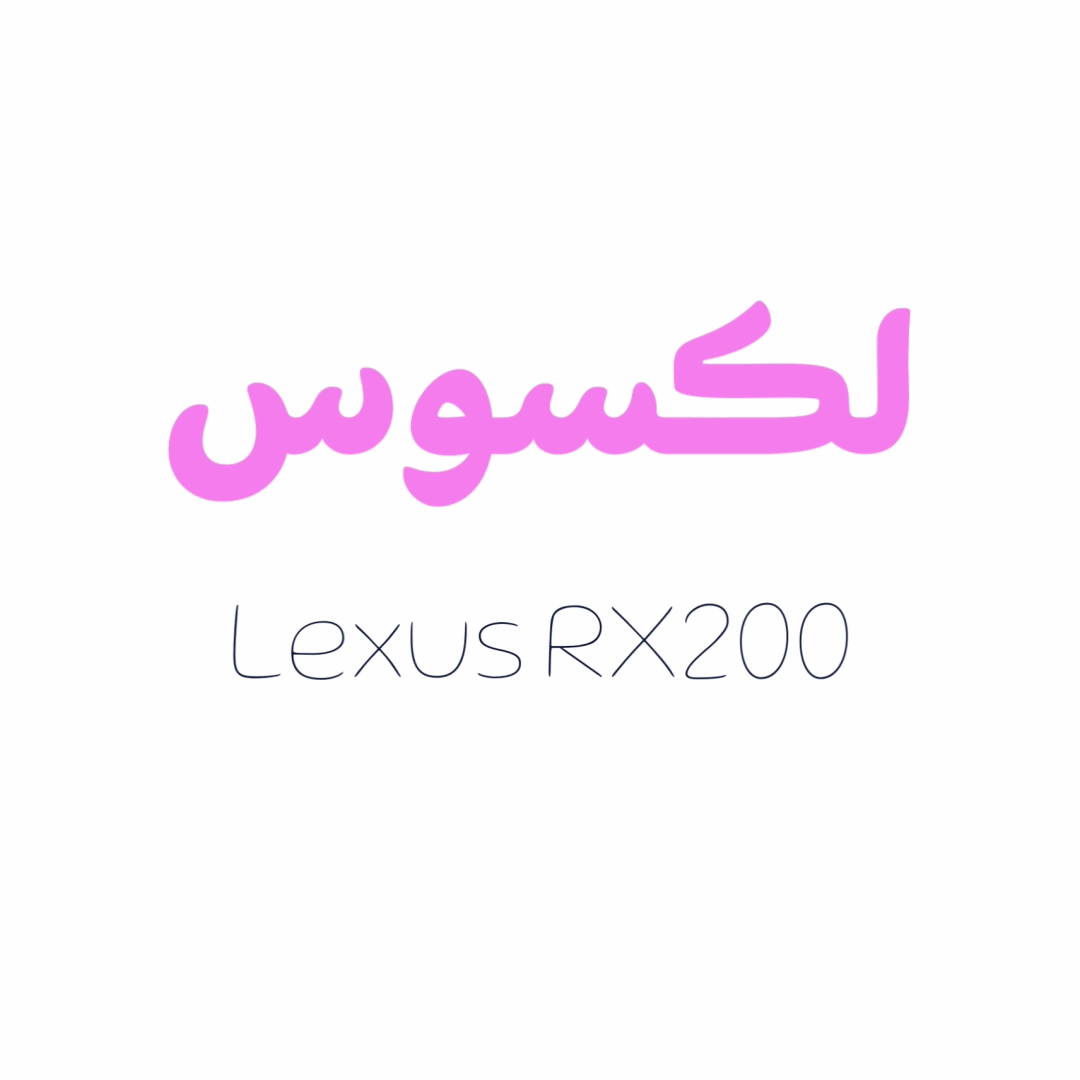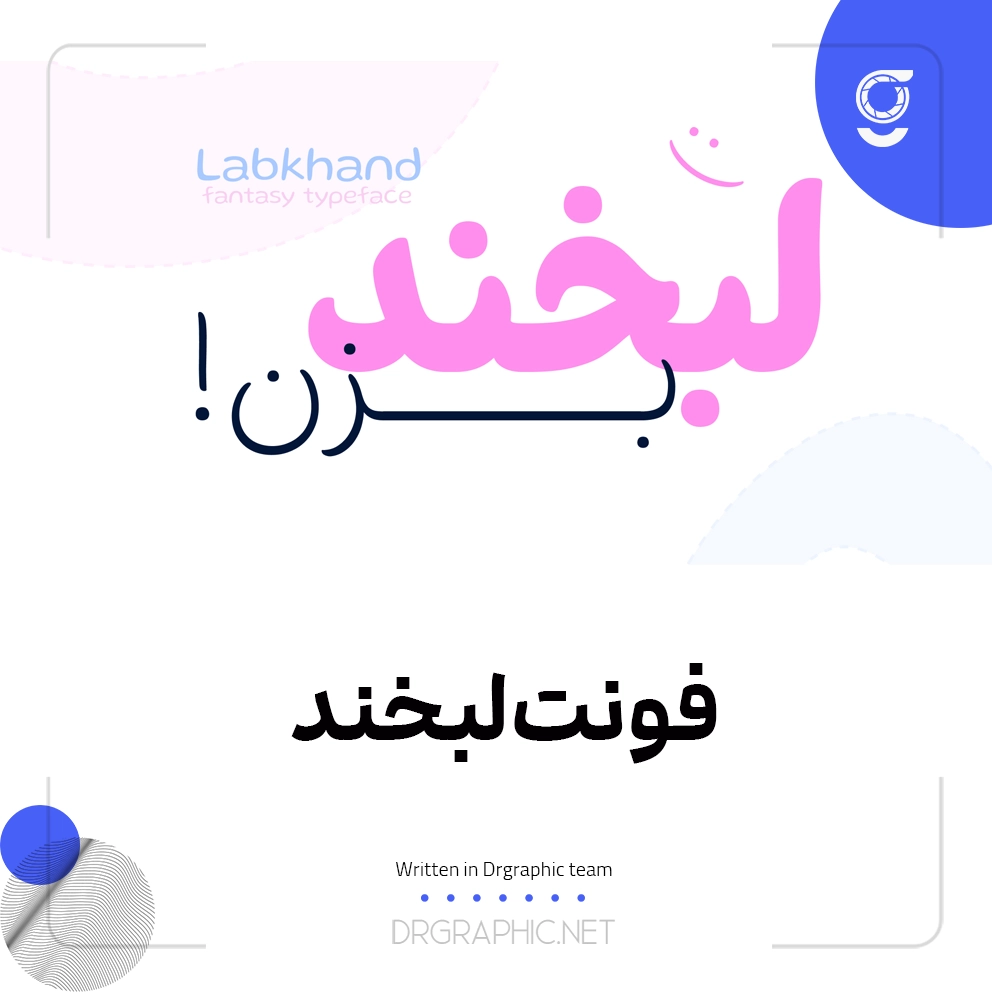
لبخند، یک فونت دستنویس فارسی است که با الهام از سادگی، صمیمیت و حالوهوای نوشتههای شخصی شکل گرفته است.با دکترگرافیک همراه باشید.
در طراحی این فونت تلاش شده تا فرم حروف، حس لطافت و نرمی را حفظ کند؛ بهگونهای که هر کلمه، حالتی زنده، دوستانه و متفاوت داشته باشد.
فونت لبخند، برای استفاده در فضاهایی طراحی شده است که نیاز به حس صمیمیت، انرژی و شخصیت دارند؛ از پوستر و بستهبندی گرفته تا محتوای شبکههای اجتماعی، متنها، عناوین و هویتهای بصری.
لبخند؛ جایی که نوشته، فقط خوانده نمیشود؛ بلکه حس میشود.
فونت لبخند دارای 6 وزن، وریبل فونت و همچنین از زبانهای فارسی، عربی، اردو، کوردی، جاوی و انگلیسی پشتیبانی میکند. لبخند مناسب تیترها، عناوین، متنهای فانتزی، فضای تبلیغاتی و فضای مجازی است.